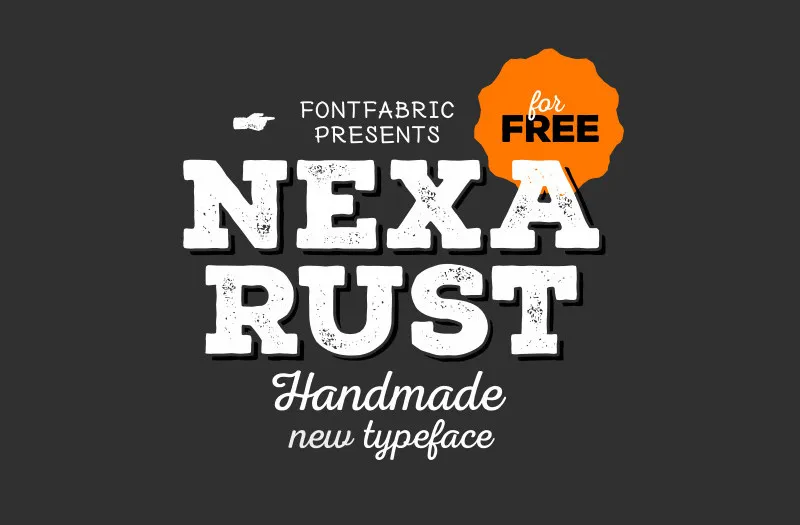
Nexa Rust Font Family – Fonte Grátis
Nexa Rust Font Family
Nexa Rust é uma fonte completa que incorpora várias sub-famílias – Sans, Slab, Script, Handmade e Extras – formando um sistema multifacetado. Esta fonte apresenta um design distintivo, com traços grossos e suaves, dando um aspecto quente e irregular aos textos. Cada uma dessas sub-famílias inclui várias pesos de fonte que se destacam por seu olhar amarelo vibrante e um leve acréscimo de saturação. É uma escolha perfeita para designers que buscam criar ambientes decorativos, especialmente em projetos onde o destaque é essencial e o contraste visual é fundamental. Com Nexa Rust, transforme seus designs textuais em verdadeiros elementos de design, adicionando um toque único e sofisticado.